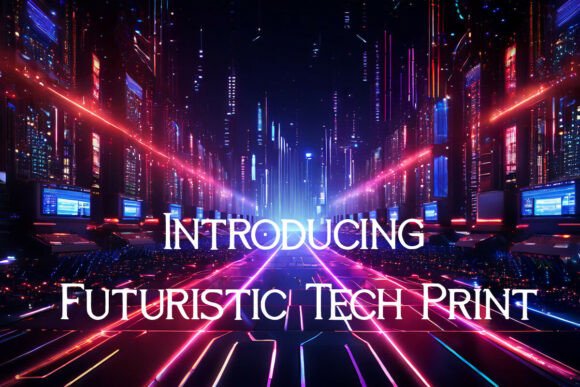
Futuristic Tech Print
Jika anda sedang mencari aset berkualiti tinggi seperti Futuristic Tech Print, pakej premium ini merupakan pilihan yang hebat untuk projek kreatif anda.
Sama ada anda mencipta produk POD (Print on Demand), jemputan perkahwinan atau grafik media sosial, Futuristic Tech Print amat bersesuaian.